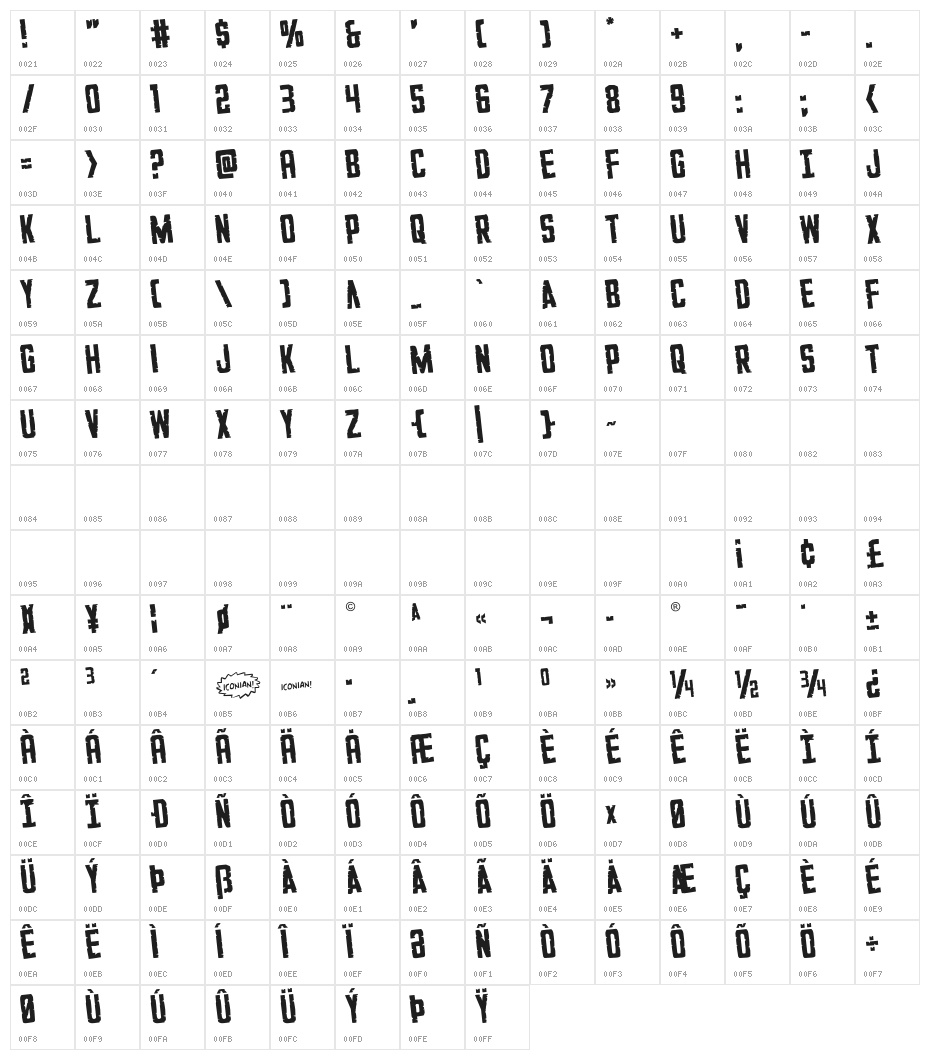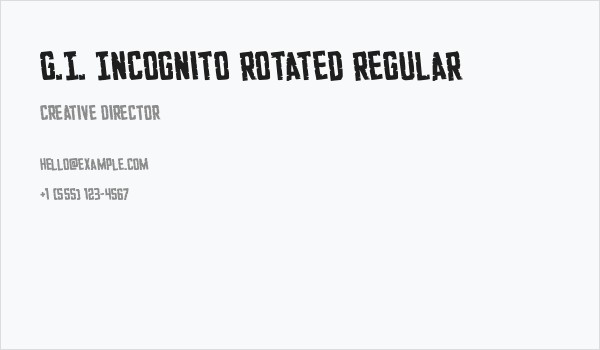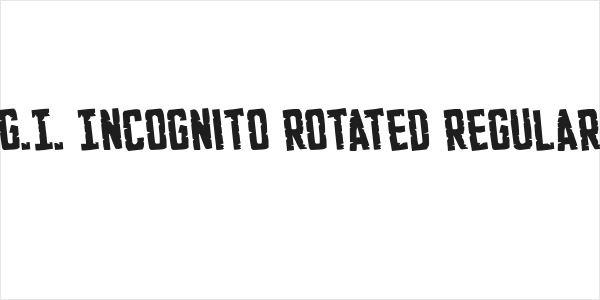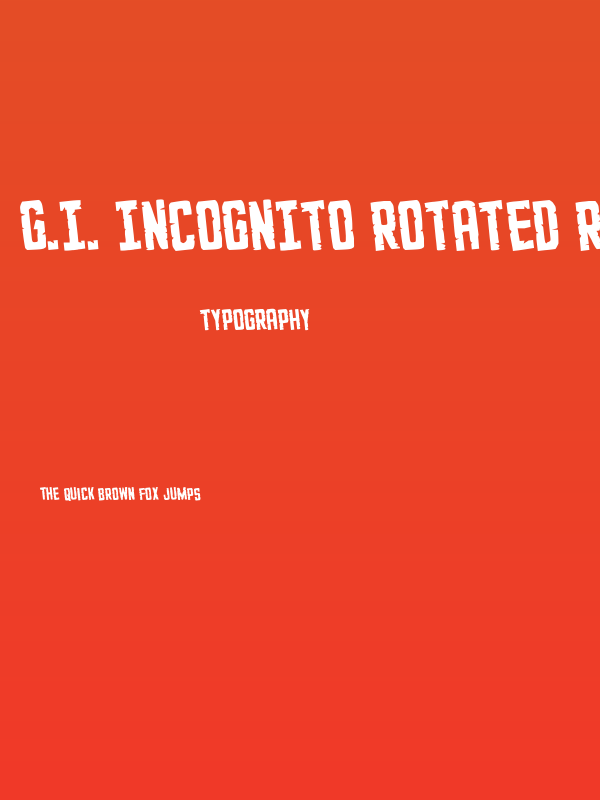
G.I. Incognito Rotated Regular Font
✎ Distorted Eroded
| Categorie | Distorted Eroded |
| Progetti proposti | Ideal for posters, album covers, video game graphics, and branding that requires a bold, impactful look. |